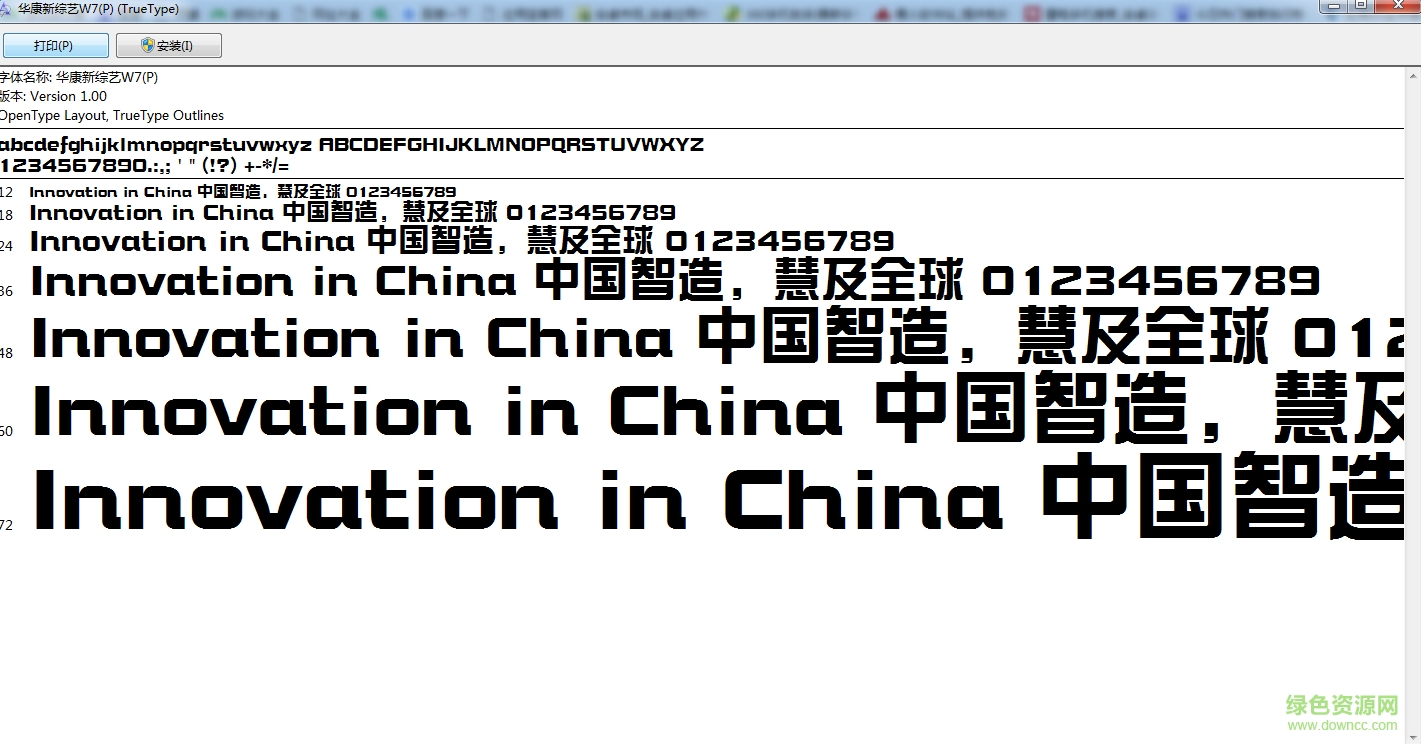
dfpzongyiw7字體是使用非常廣泛的一款字體,我們經(jīng)常能在影視作品開頭那些logo字體,還有廣告設(shè)計的大字體看到這個字體,這個字體使用非常的廣泛,而且字體也確實很漂亮,喜歡這個字體的用戶,快來綠色資源網(wǎng)下載吧!
dfpzongyiw7字體又叫華康新綜藝w7字體,字體飽滿,渾厚婉轉(zhuǎn),用途廣泛,適用于策劃設(shè)計、包裝設(shè)計、廣告設(shè)計、影視影視等眾多領(lǐng)域。
dfpzongyiw7是一套常見及常用的POP廣告字體,以黑體為基本出發(fā)點,外觀更趨方正,外張,結(jié)構(gòu)與筆劃更善于平均分布,擺脫了傳統(tǒng)黑體之規(guī)范,更具自由。